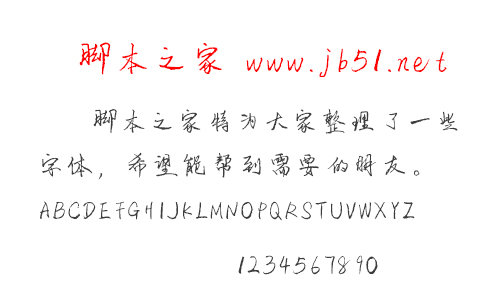
麥撲鋼筆行書簡體是一款用于書法設(shè)計(jì)方面的字體,可以作為鋼筆行書字帖的好字體,該字體線條優(yōu)美,就像寫出的鋼筆字一樣,非常漂亮,適合應(yīng)用于藝術(shù)設(shè)計(jì)、平面宣傳設(shè)計(jì)、網(wǎng)頁設(shè)計(jì),書法字帖等領(lǐng)域,歡迎喜歡麥撲鋼筆行書簡體的朋友前來下載使用。